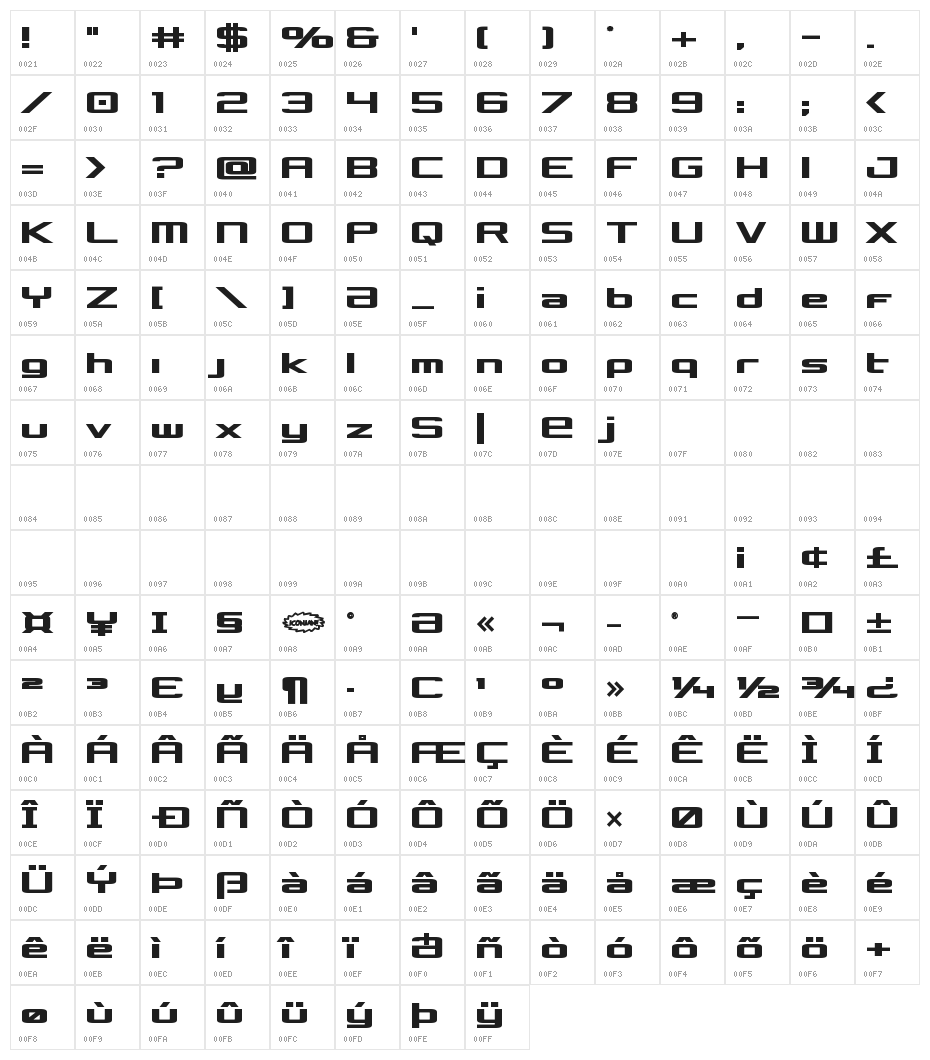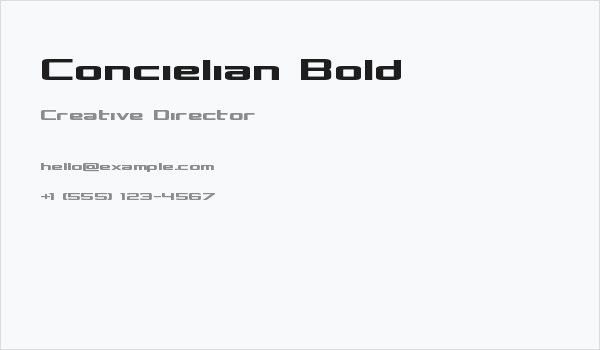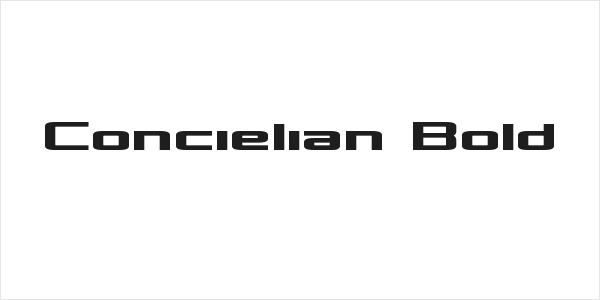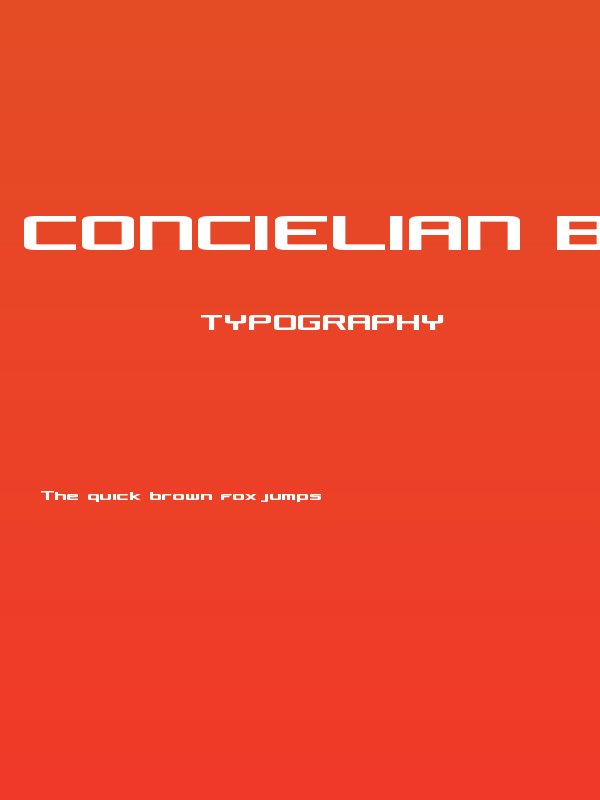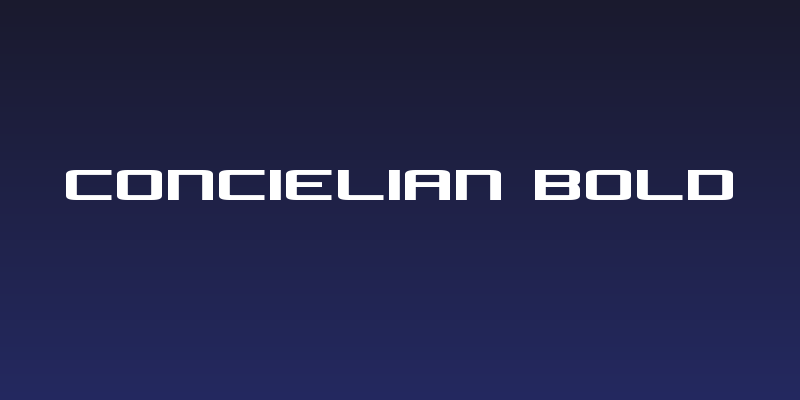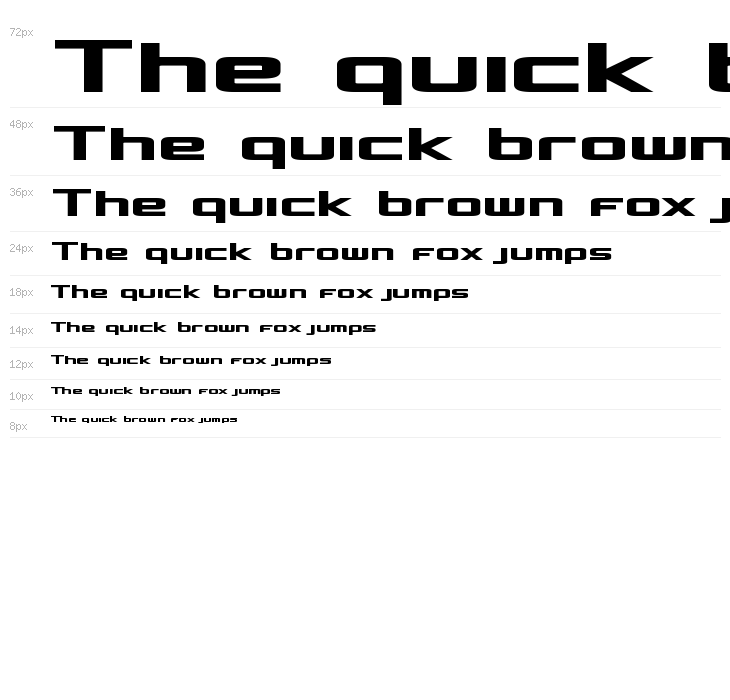
Concielian Bold Font
✎ Futuristic
| 分类 | Futuristic |
| 使用场景 | Headlines, Logos, Digital Displays |
| 推荐项目 | Ideal for technology branding, digital interfaces, video game graphics, and futuristic-themed posters. |